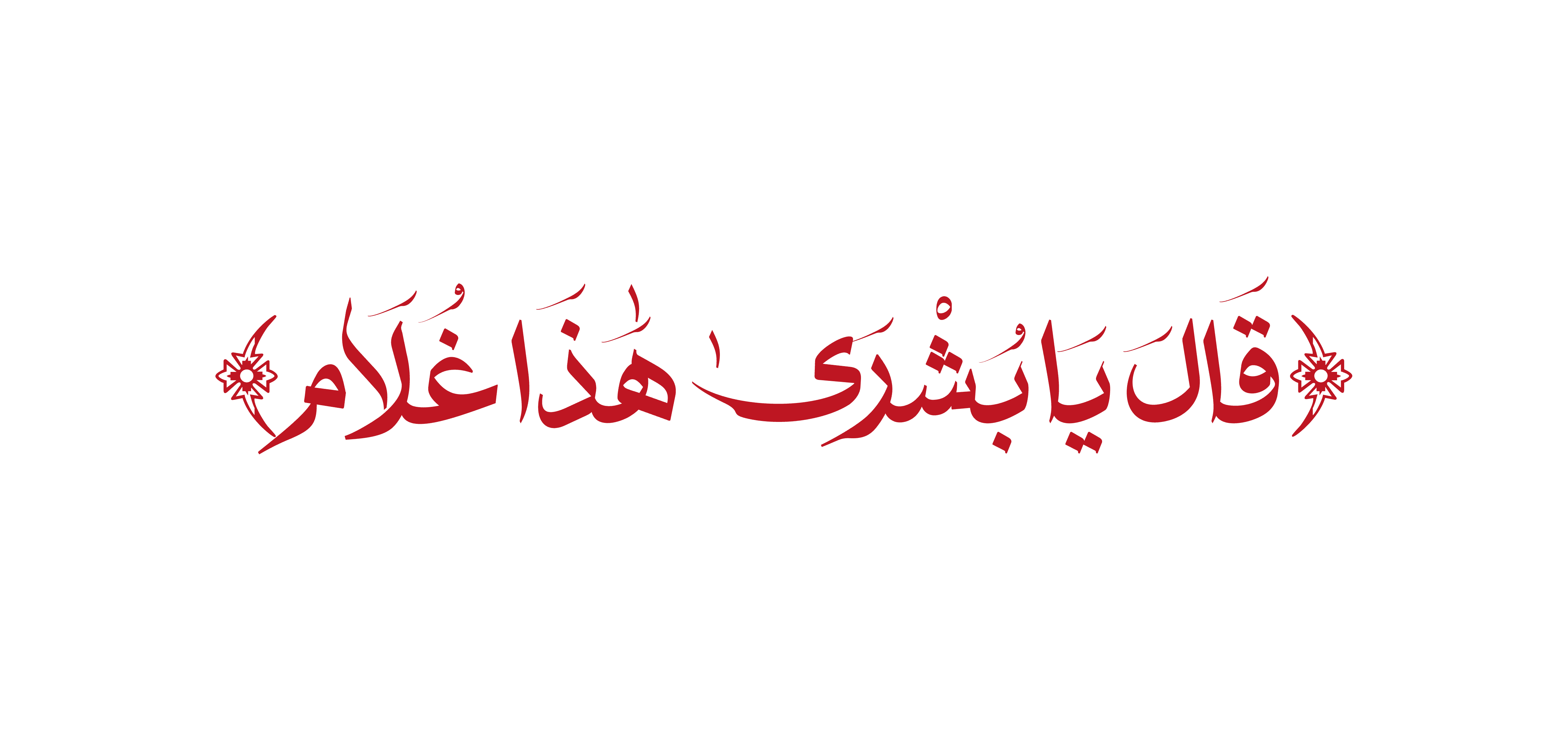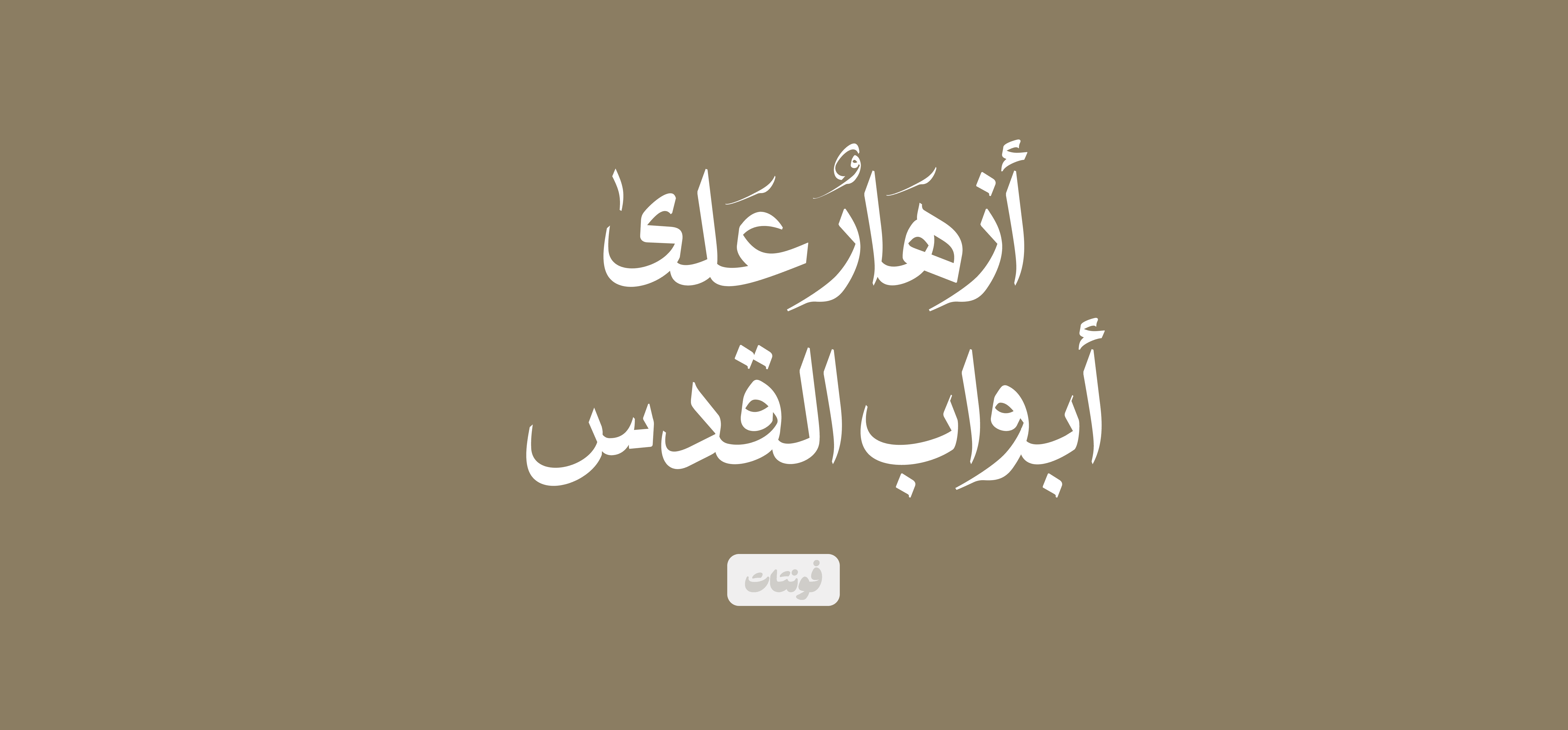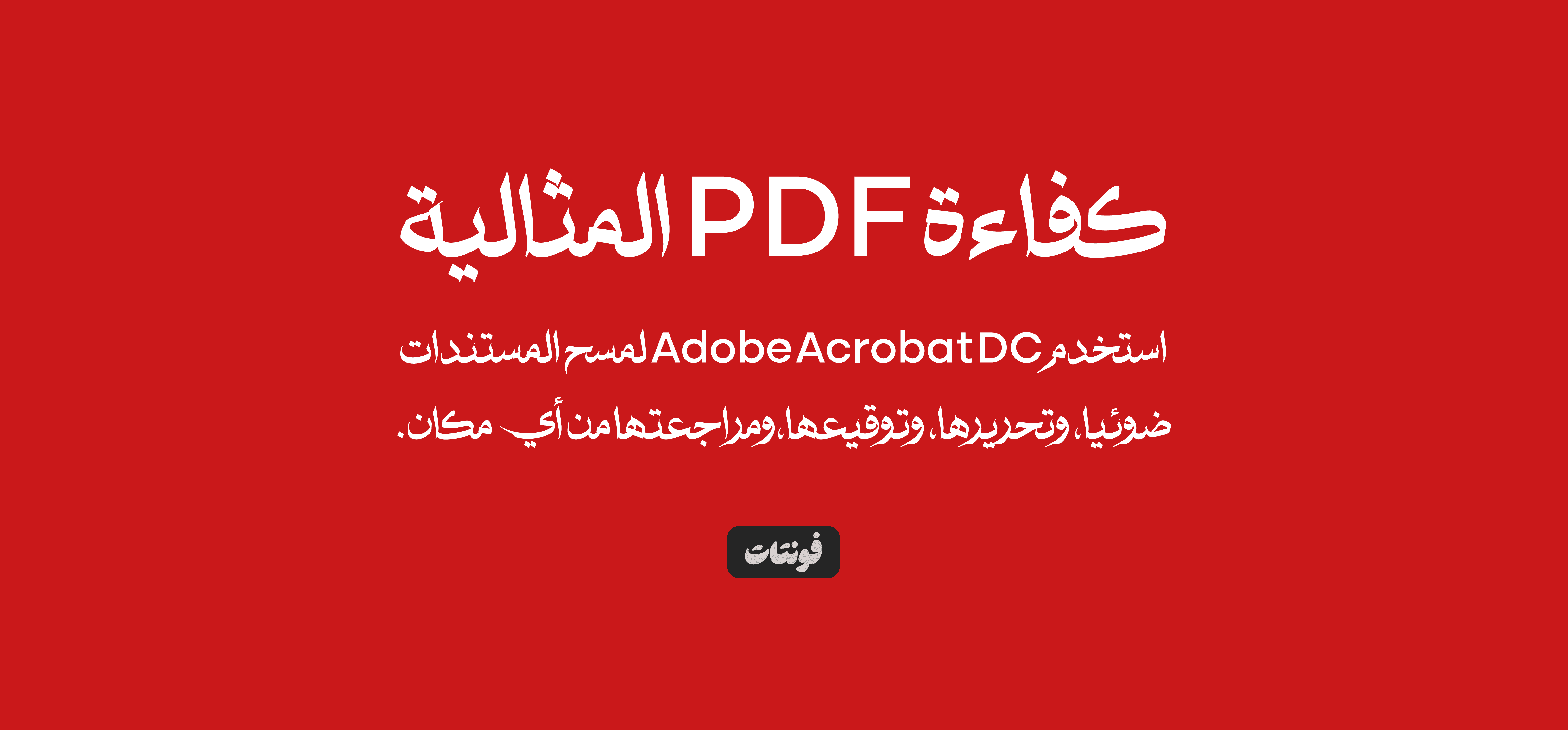
RTL Bushra - خط بشرى
الاوزان: وزن واحد
اللغات: العربية, الفارسية
بشرى، خط عنونة ونصوص، متوسط، من وزن واحد، متعدد اللغات، يعمل في كافة البيئات التشغيلية.